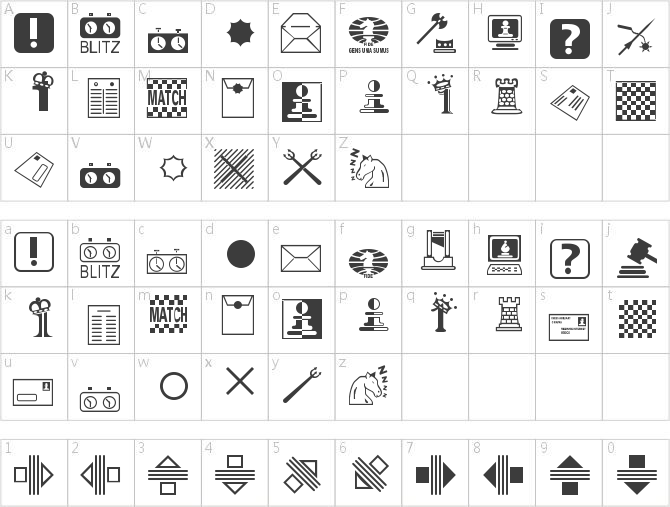
Chess Miscel 詳情頁
字體名稱: Chess M
Chess Miscel
Chess Miscel介紹
Chess Miscel字體字庫是一款讓人賞心悅目、百看不厭的英文字體,適合各類廣告和產品包裝設計應用,字體大小0.07MB,格式為ttf字體,上傳用戶是浪跡天涯,作者/版權方為未知